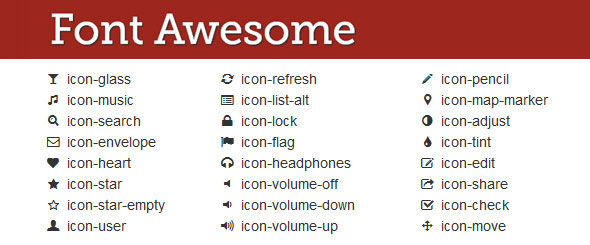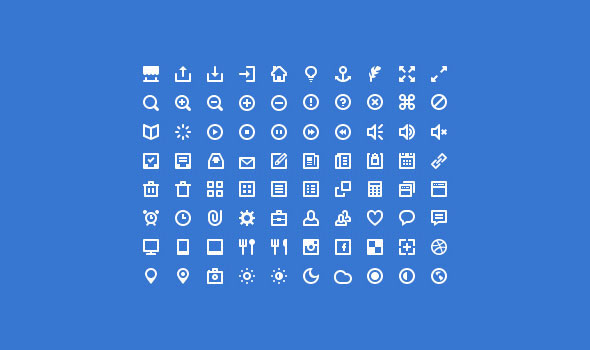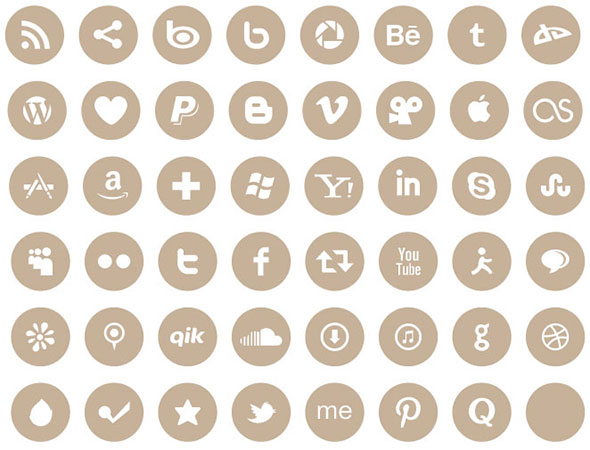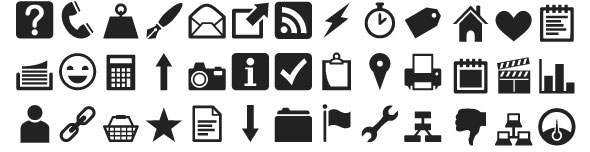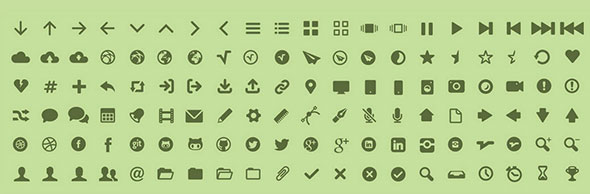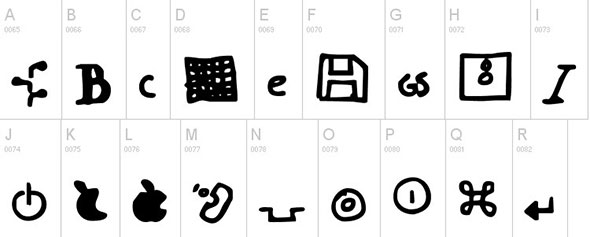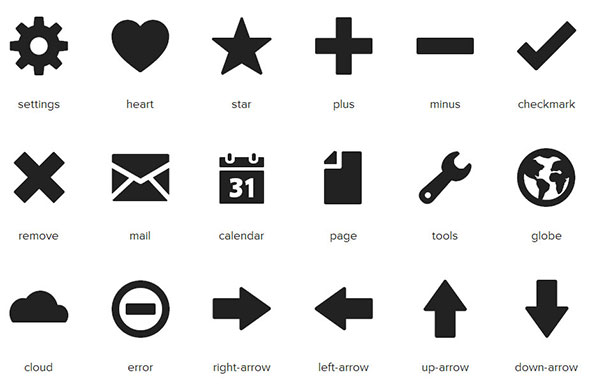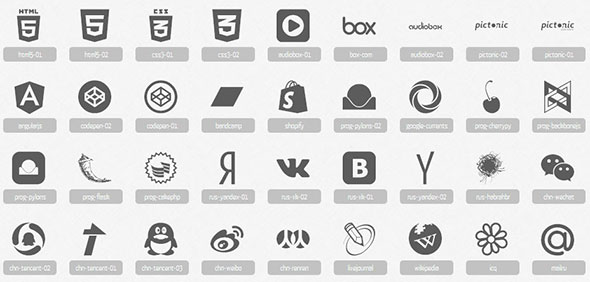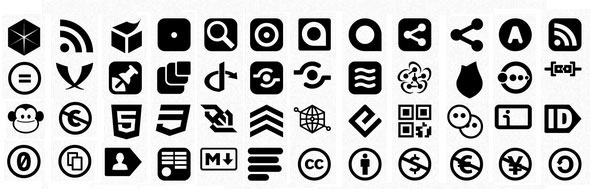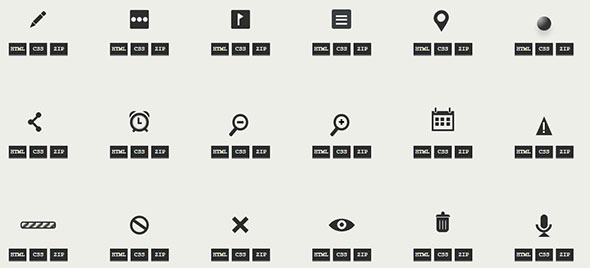
Бесплатные шрифты-пиктограммы
Сегодняшняя подборка бесплатных иконок посвящена шрифтам-пиктограммам. Такой вариант удобен, если вам нужно использовать иконки в большом количестве и в разных местах. Весят они куда меньше, чем растровые изображения, а редактировать их можно прямо в таблице стилей. Все наборы шрифтов в подборке бесплатные. Так что свободно качайте и используйте понравившиеся!
Awesome Font
MFG Labs
Foundation Icons
Pictonic
Openweb Icons
One Div
PW Drawn
Web-symbols
Rondo
80 mini icons
Fontelico
Social media icons
Social logos
APP icon font http://www.heydonworks.com/article/an-app-icon-font
JustVector Social Icons Font
Brandico
Stateface
Geobats
Dotcom